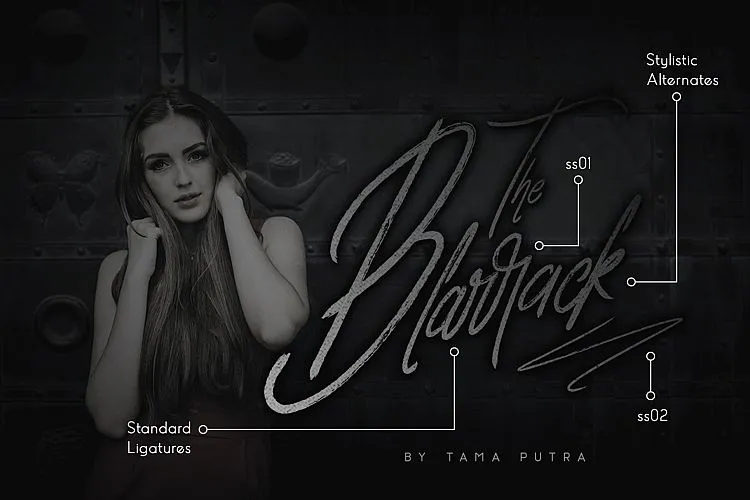
Blarrack Script Font Duo – Download Grátis
A Blarrack Script Font Duo é uma nova dupla de fontes script e grafia manuscrita criada pelo designer Tama Putra. Este conjunto de fontes moderno e vintage é feito a mão, oferecendo linhas monolineares para tipografia visualmente impactante e versátil. As Blarrack Script Font Duo são ideais para uma variedade de projetos, desde logotipos, ilustração à estamparia, labels e até mesmo posters. Elas se adaptam perfeitamente a várias necessidades gráficas, oferecendo um toque moderno ao seu design, com o charme vintage característico das fontes script. Perfecto para quem busca uma combinação de elegância e frescura em suas criações.